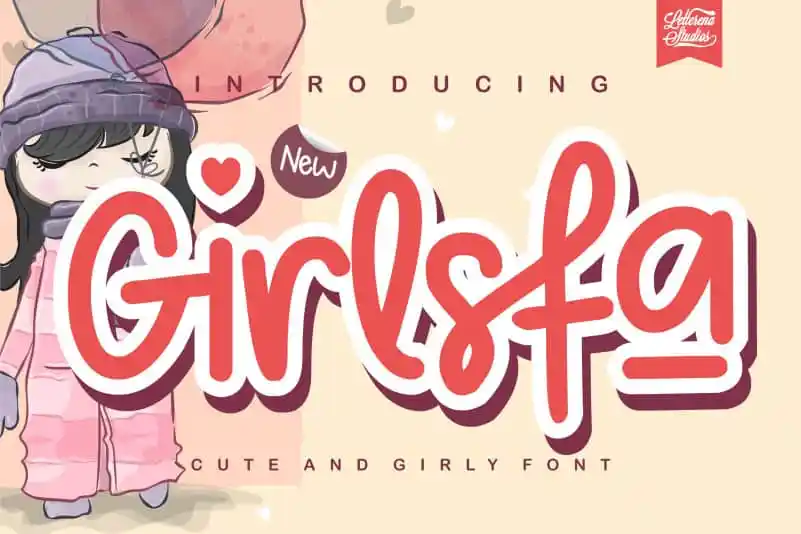
Girlsfa – Cute and Girly Font – Download Grátis
A Girlsfa – Cute and Girly Font é uma fonte elegante e delicada criada pelo designer letterenastudios para quem aprecia elementos femininos na tipografia. Ela oferece um ar fresco ao design de qualquer projeto graças às suas linhas suaves, tonalidades alegres e traços levemente curvados. Com uma aparência que parece escrita à mão, esta fonte cria um toque personalizado em textos como cartões de aniversário, mensagens de texto ou até mesmo nomes infantis nas escolas. Proporcionando um charme único ao seu design gráfico, Girlsfa é perfeita para atender a clientes fashion sensíveis e apaixonados por estilos delicados. Além disso, ela atende à nossa categoria de Handwritten Fonts, garantindo que seus projetos tenham uma aparência autêntica e pessoal. Essa fonte personalizável é um ótimo complemento para qualquer designer que busca um toque feminino em suas criações digitais. Com a exclusividade do uso pessoal (sem fins comerciais), Girlsfa – Cute and Girly Font oferece à você designers, freelancers e estilistas um recurso versátil para personalizar seus projetos de forma original e autêntica. Não se esqueça de respeitar as regras de uso exclusivamente pessoal desta fonte quando incorpora-a em seu trabalho.